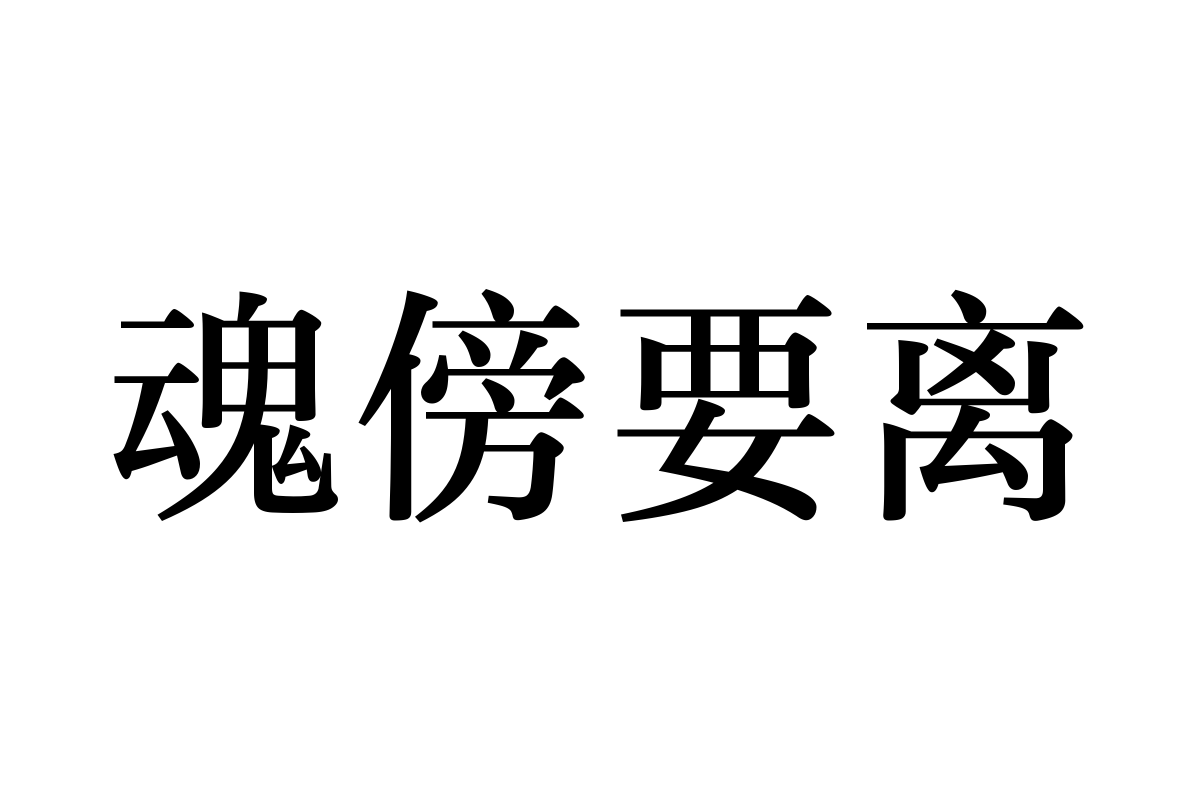
汉仪玄宋 55S 是一款具有现代感的中文字体,适用于各种商业、学术和设计项目。这款字体的设计灵感来源于传统的书法艺术,但又融入了现代元素,使其更加简洁、易读。
汉仪玄宋 55S 的特点包括:
– 优雅的笔画线条,呈现出一种流畅而自然的美感。
– 独特的字形结构,使得文字在视觉上更具冲击力和辨识度。
– 多种字重可供选择,满足不同场景的需求。
– 适合用于标题、正文、广告、标志等多种场合。
总的来说,汉仪玄宋 55S 是一款非常实用且具有特色的中文字体,无论是在商业还是设计领域都能发挥出其独特的魅力。